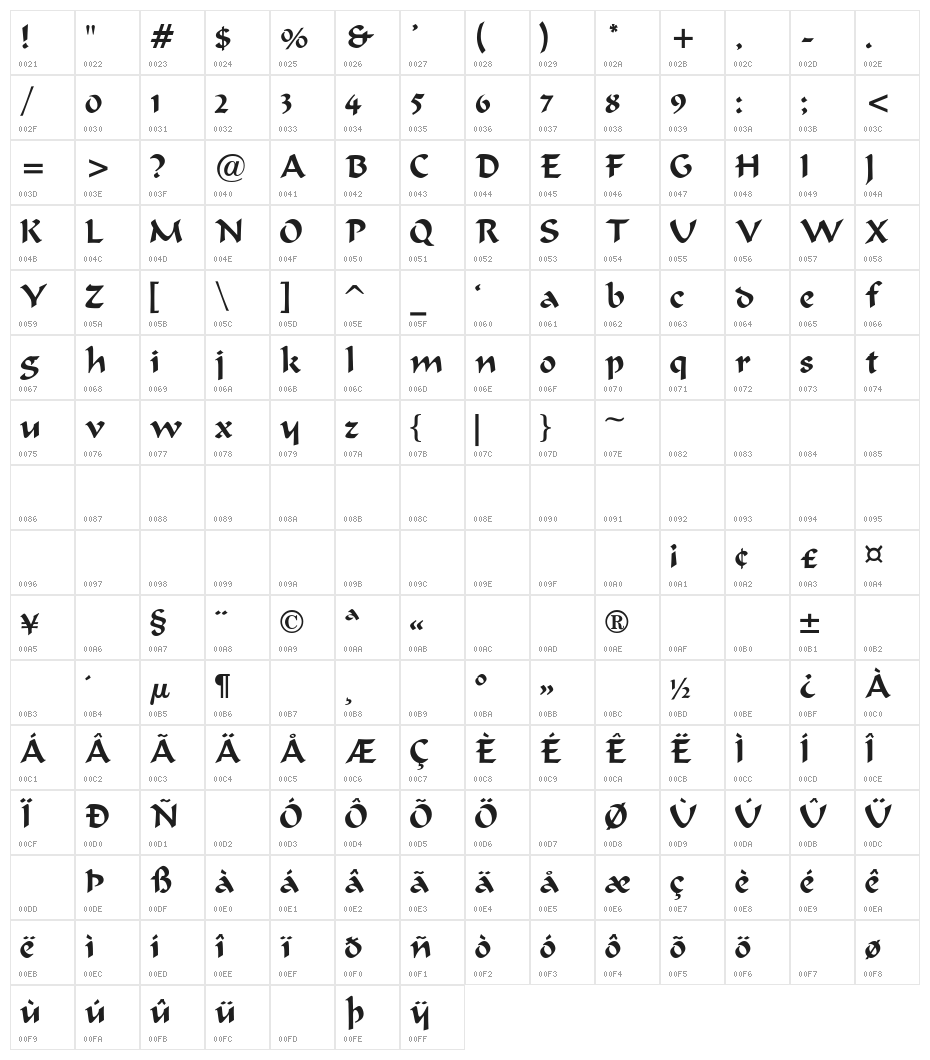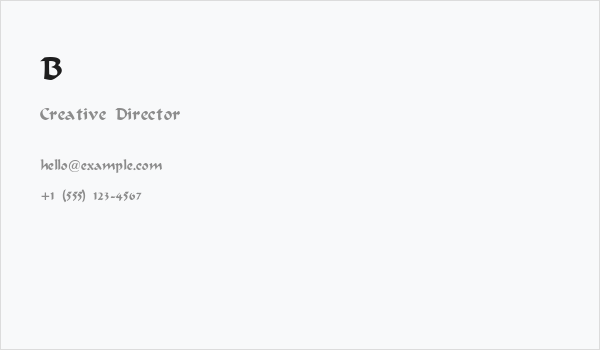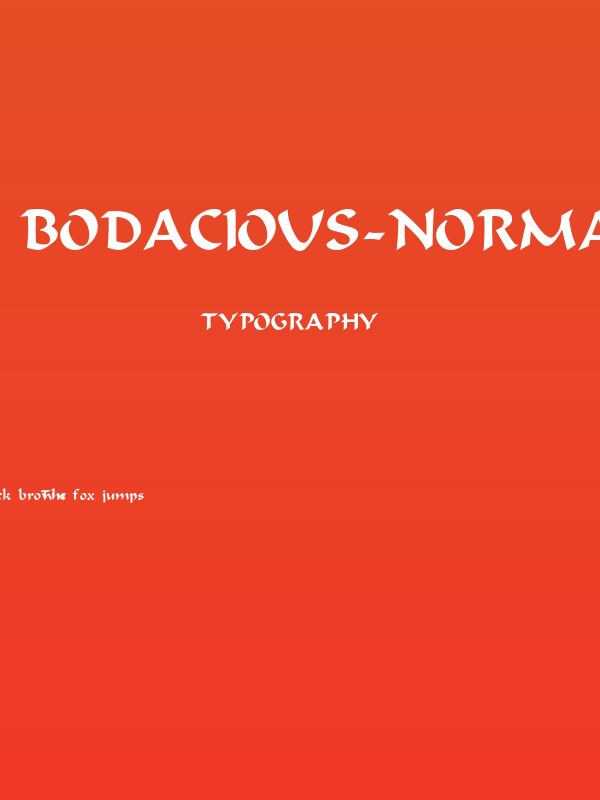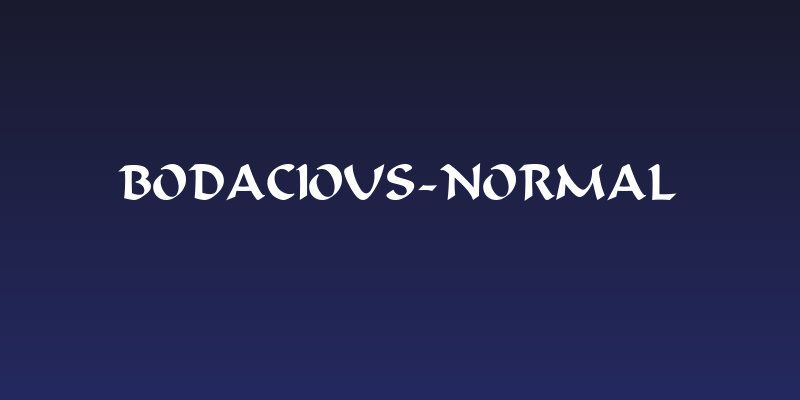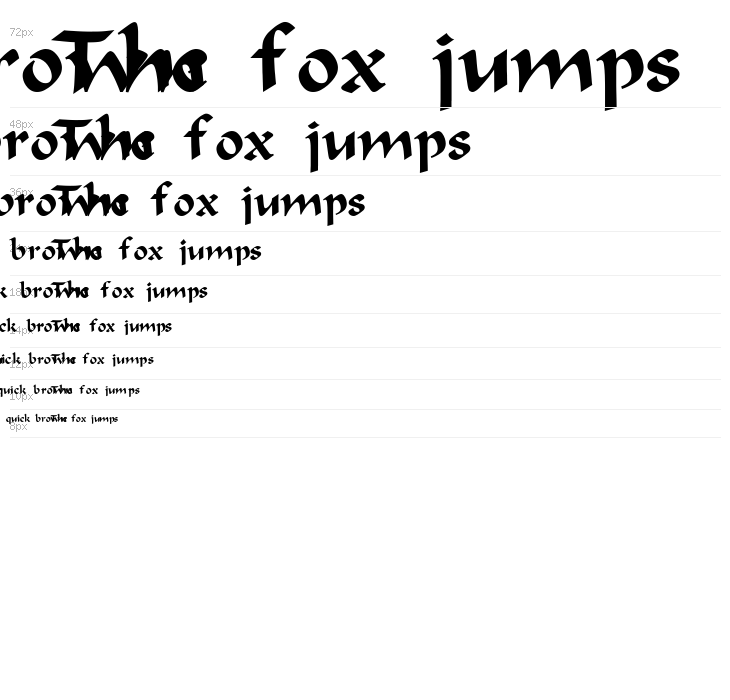
Bodacious-Normal Font
✎ Calligraphic
| Kategorien | Calligraphic |
| Gesamtstil | Medieval, Decorative |
| Vorgeschlagene Projekte | Ideal for fantasy book covers, medieval-themed event posters, and video game graphics. |